Neue und vielfältige Möglichkeiten des Buchobjekts dachten sich die Studenten des Illustrationskurs der Hoschschule für Gestaltung Offenbach aus und präsentierten sie im Klingspor Museum in Offenbach am 12.–14. November 2004. Die Ausstellung nannte sich »Das Klapp-, Falt-, Objektbuch«.
Zwei Arbeiten von TypeOff Mitgliedern befanden sich unter anderem in dieser Ausstellung. Dan Reynolds Arbeit, ein überdimensionales Blatt handgezeichnet mit seiner neuen Schrift Farewell, nannte sich Lettering Eric Gill’s »On Lettering«. Ein beruhigendes und gleichzeitig beeindruckendes Schriftbild wurde könnend dargestellt.
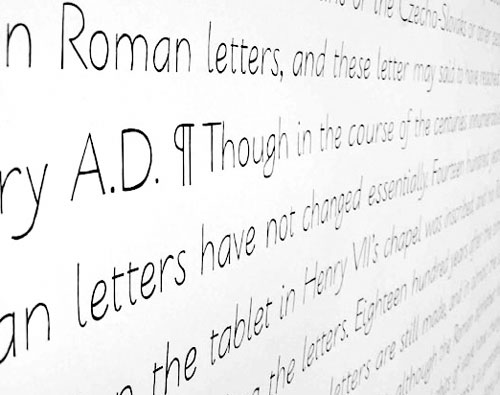
Nachdem Reynolds Monate lang daran gearbeitet und sich Blasen an den Fingern geholt hatte, konnte er sich auf seinem Schriftbett wahrlich ausruhen.
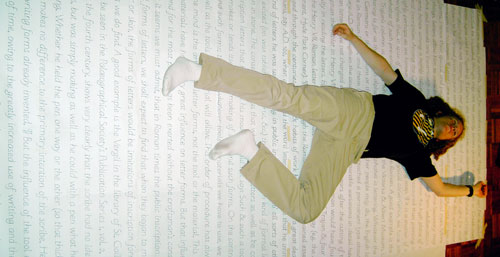
Lara Glück baute einen aufklappbaren Kubus, der den antiken Mythos von Io und die aktuelle Situation des Datenschutzes verband. Sie benutzte die extra für den Zweck entworfene Schrift Argos.
Von einem komplett flachen Zustand, entfaltete sich die Geschichte, sodass am Ende die haptischen Seiten des Mythos sich außen und die Bilder der Überwachungstechnologien sich innen befanden.
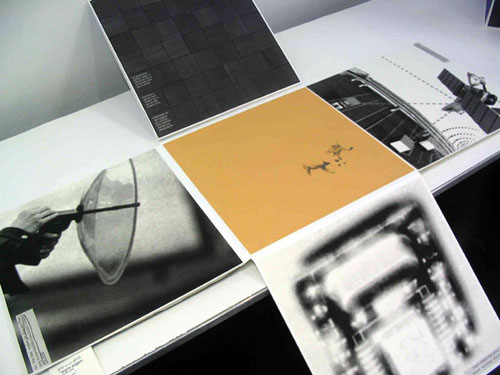
Reynolds und Glück entwarfen zusätzlich das Austellungsplakat. Der Entwurf sah vor, dass vier verschiedene DIN A3 Plakate allein darstehen konnten, zugleich aber auch ein größeres Plakat ergeben konnten. Im zusammengesetztem Zustand formten die orange-farbigen Flächen der vier Plakate den Buchstaben »b«, um eine Assoziation an das Buch hervorzurufen.